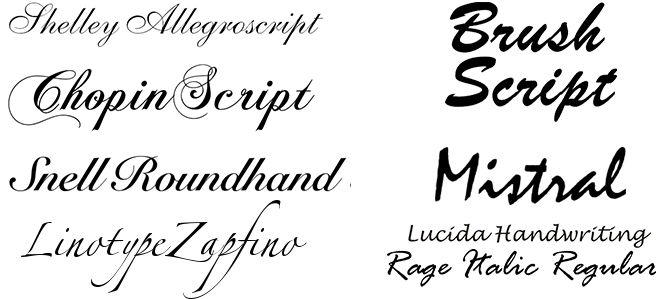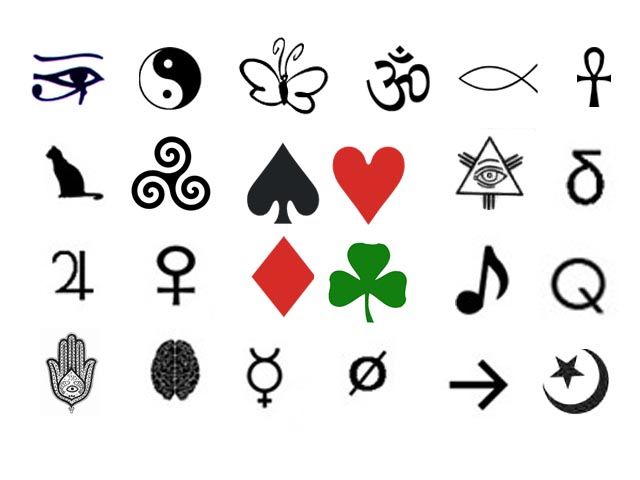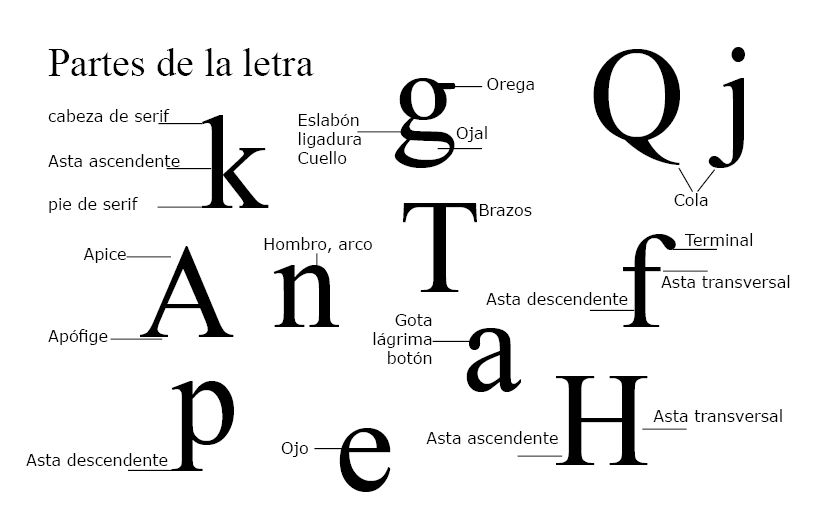
Tipografia
partes de una letra
Tipografia
Que es?
es el fiel reflejo de una época.
es el arte de diseñar letras y componer texto de tal modo que puedan leerse de un modo fácil, eficaz y agradable.
DESARROLLO DE LA ESCRITURA ►PICTOGRAMAS ►MUTACIÓN A UNA FORMA ALFABÉTICA► VARIACIONES DEL ALFABETO
Caracteres pueden ser:
Partes de una letra